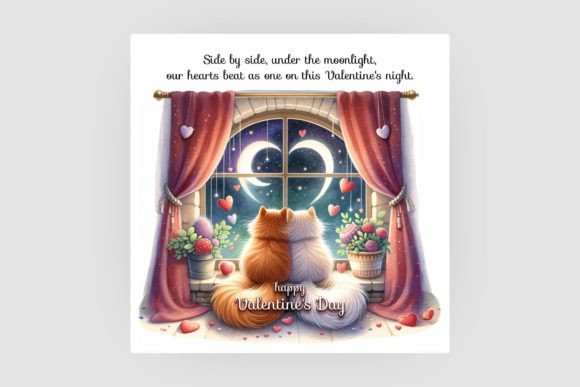
Valentine’s Day Greeting Social Media
Ulasan Detalhada: Template de Postagens para Redes Sociais – Saudações de Dia dos Namorados
Se você procura a combinação perfeita entre design elegante e facilidade de personalização para celebrar o Dia dos Namorados nas redes sociais, o Valentine’s Day Greeting Social Media Post Template é a escolha ideal. Este modelo, pronto para download, foi criado especialmente para quem deseja transmitir amor e calor em cada publicação, sem perder tempo com ajustes complicados.
- Fonte Sofia (Google Font) – Tipografia moderna e romântica que garante legibilidade e estilo.
- Imagem incluída no design – Elementos visuais prontos para uso, otimizados para atrair curtidas e compartilhamentos.
Ao baixar este template, você recebe um arquivo .psd completo, pronto para ser adaptado ao seu público. Seja enviando mensagens de amor para clientes, parceiros ou seguidores, a estrutura flexível permite inserir seu próprio texto, logotipo ou até mesmo mudar a paleta de cores para combinar com a identidade visual da sua marca.
Em resumo, o Valentine’s Day Greeting Social Media Post Template oferece:
- Design romântico e profissional;
- Facilidade de edição para quem não é designer;